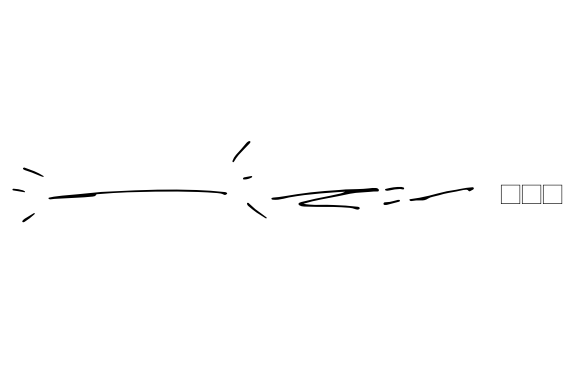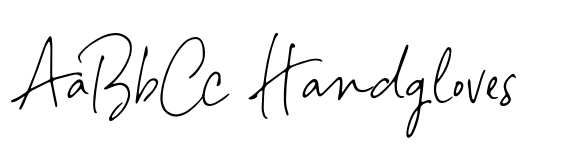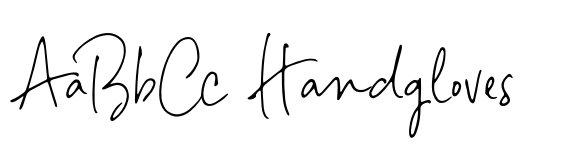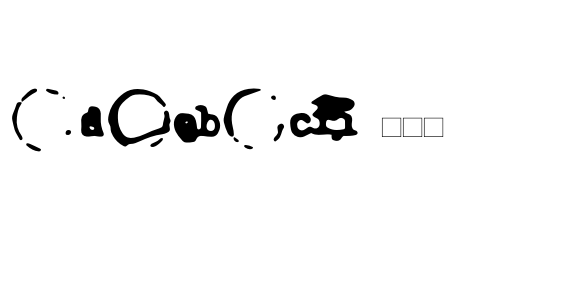
Notes and Quotes
von Ana's Fonts
Notes and Quotes Font Familie wurde entworfen von Ana Parracho und herausgegeben von Ana's Fonts. Notes and Quotes enthält 6 Stile und Optionen für Familienpakete.
Über die Schriftfamilie Notes and Quotes
Notes And Quotes ist ein Font -Duo, das eine fette Schreibmaschine Font und eine lässige Schrift Font umfasst. Der Kontrast zwischen der Fonts macht sie zu einem auffälligen Paar, das sich perfekt für Logodesign, modernes Branding und Verpackungen, Zitate und Beiträge in sozialen Medien eignet.
Notes And Quotes enthält 6 Fonts:
• eine handgeschriebene Schrift Font mit
• eine schräge Alternative und
• ein zusätzliches Set mit handschriftlichen Kritzeleien (Unterstreichungen, Kreise, Wörter und kurze Sätze usw.)
• eine fette Schreibmaschine Font mit
• eine "sprunghafte" Alternative und
• eine Reihe von zusätzlichen Fehldrucken und schmutzigen Elementen